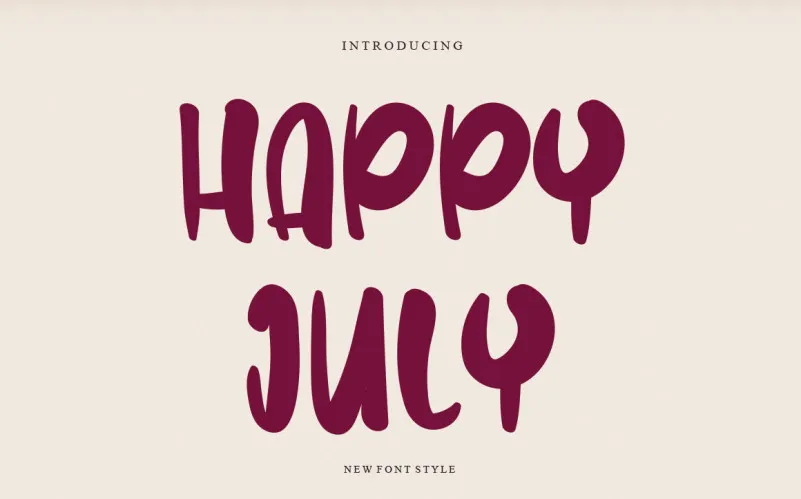
A Happy July Font é uma fonte escrita a mão única e amigável que traz diversão e simplicidade para projetos criativos. Perfeita tanto para Instagram Stories quanto para uma escritura calligráfica, esta fonte toca qualquer ideia de arte pessoal em um verdadeiro trabalho de arte! Ela é perfeitamente adaptada para quem busca tornar seus projetos mais atraentes e autênticos. Em um mundo cada vez mais digitalizado, Happy July Font oferece aos criativos uma maneira única de expressar suas ideias de forma única e personalizada. A fonte foi desenvolvida pelo designer levincreative, certificando-a como perfeita para projetos DIY.